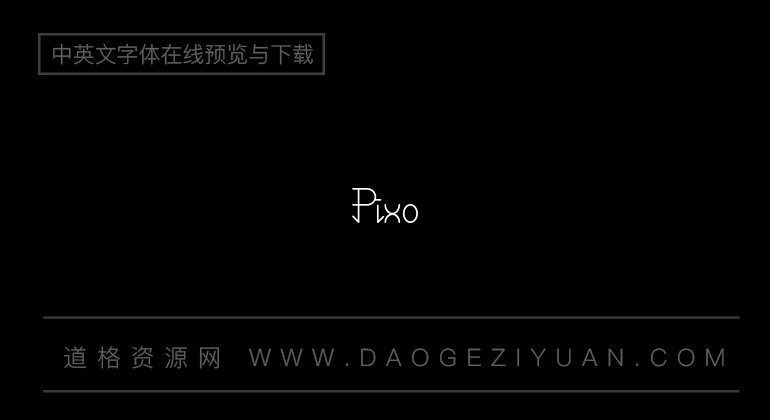
Pixo 是一种免费的无衬线字体,由 Craig Black 设计。它的特点是简洁、现代和极具可读性。Pixo 字体在各种设计项目中都非常实用,如品牌标识、海报、标语、包装设计等。 Pixo 字体家族拥有多种字重和变体,包括常规、粗体、斜体、斜粗体等,以满足各种设计需求。此外,该字体还支持多种语言,使它成为一个功能强大的全球化设计工具。 总的来说,Pixo 字体是一种非常实用的现代字体,适用于各种设计项目,无论是数字还是印刷媒体。内容介绍
Pixo是一款非常不错的手写艺术字体,具有很好的视觉感,适合于文化类的宣传设计、商业类品牌的广告和产品包装设计以及个性化文字排版等较多场景。